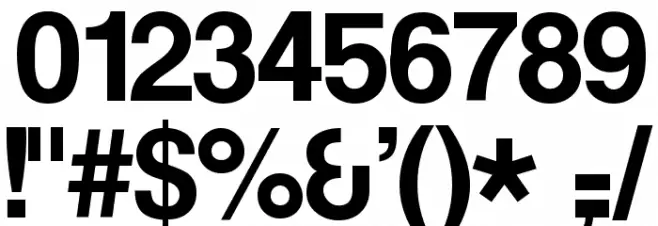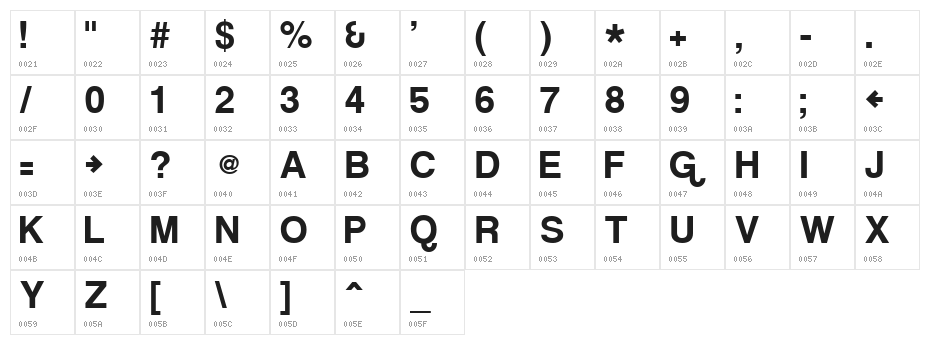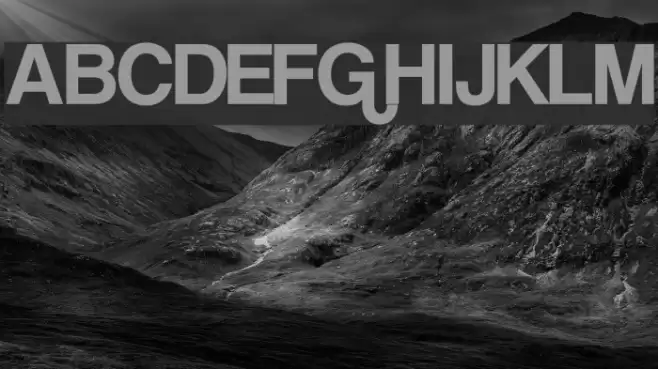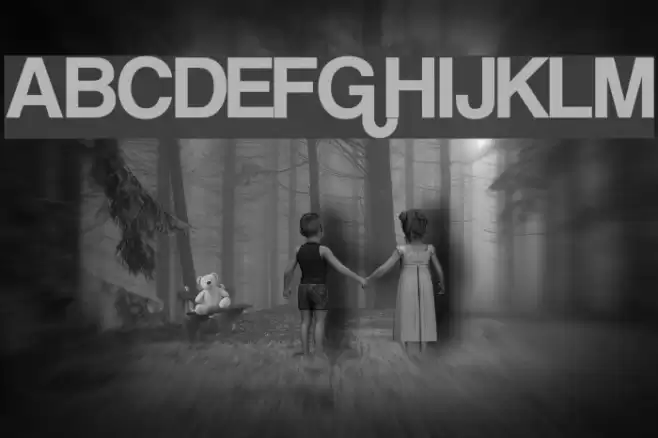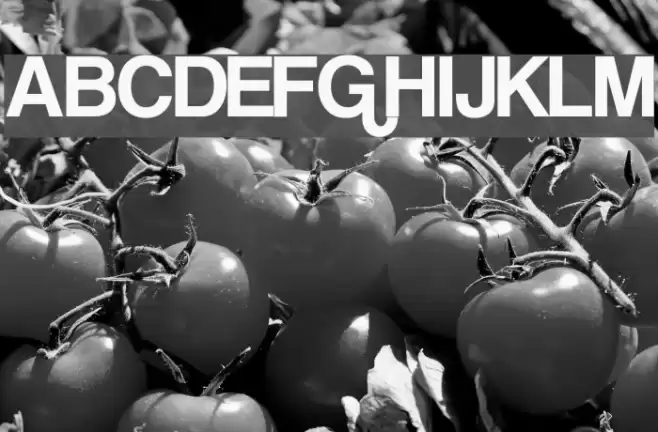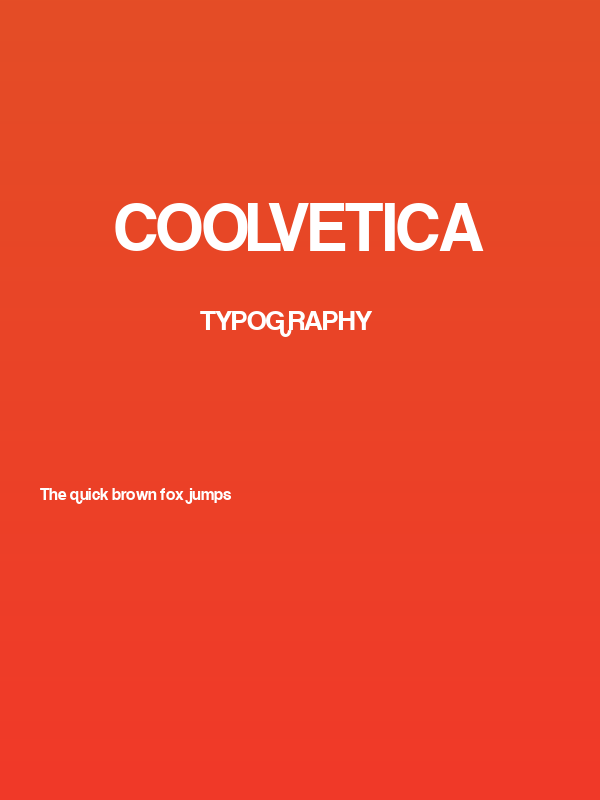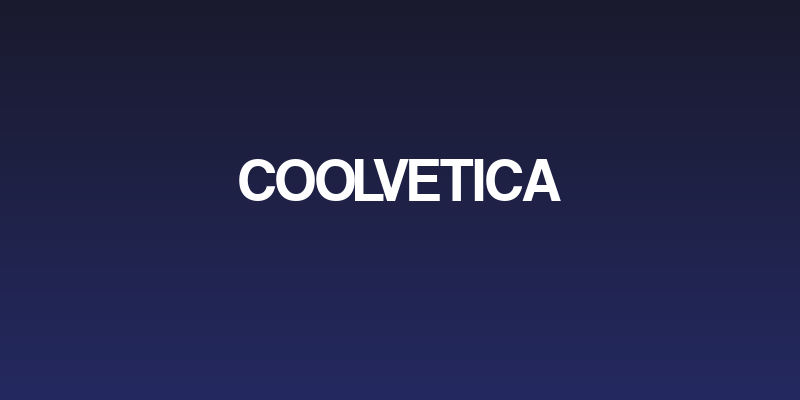
Coolvetica Font
| カテゴリ | Formal |
| 用途 | Headlines, Logos, Branding |
| おすすめプロジェクト | Ideal for branding, advertising, web design, and editorial projects that require a bold, modern touch. |